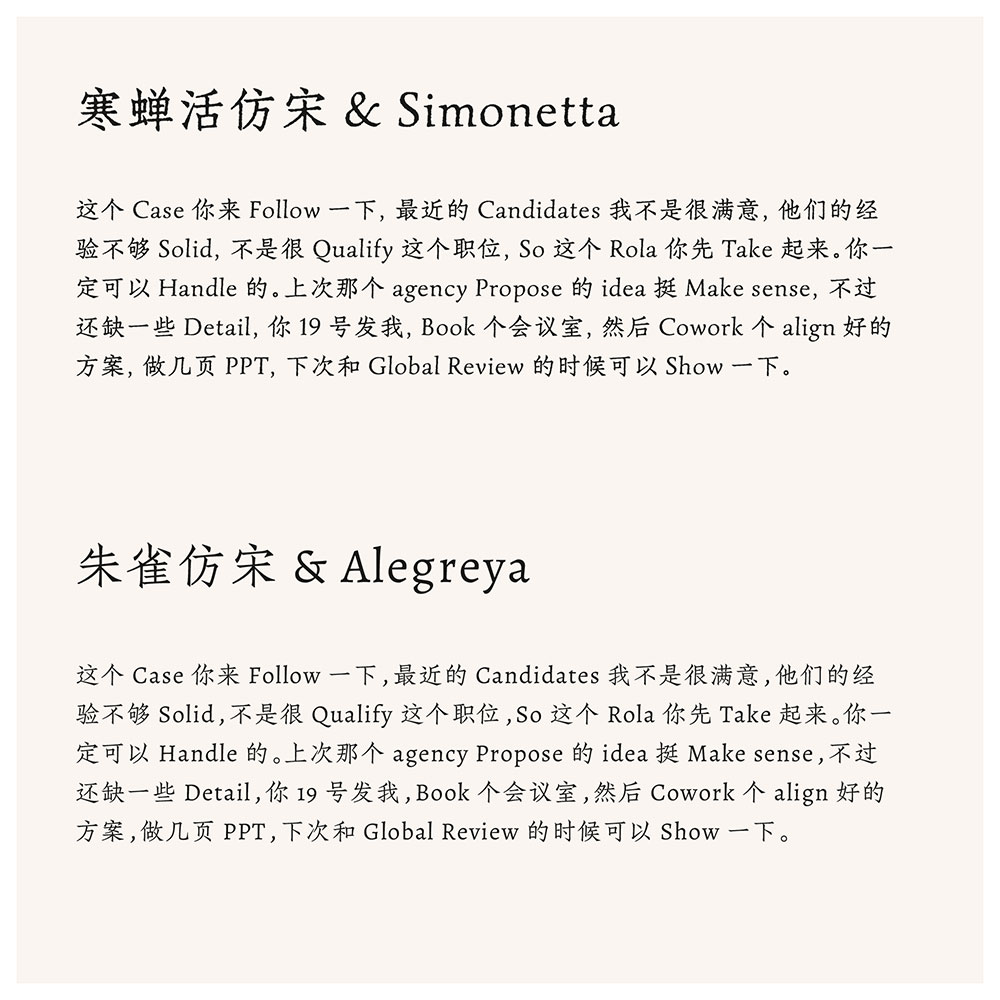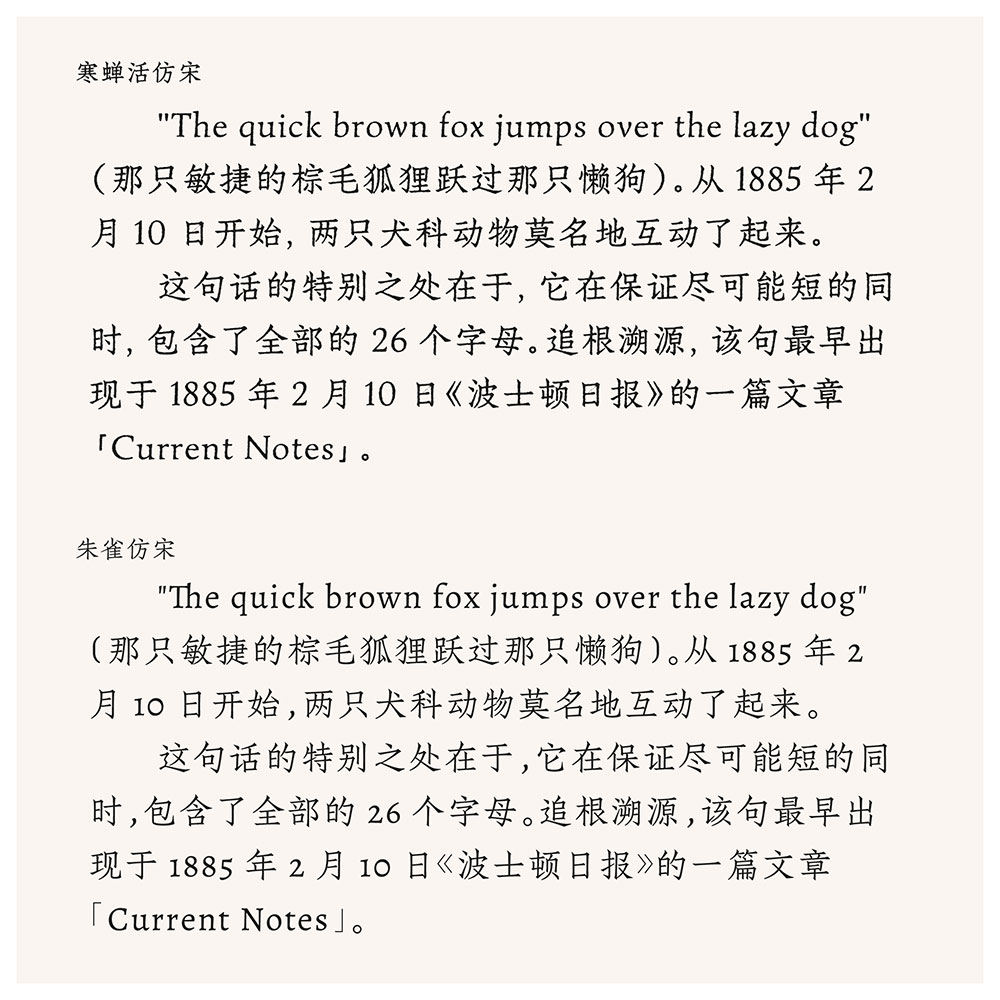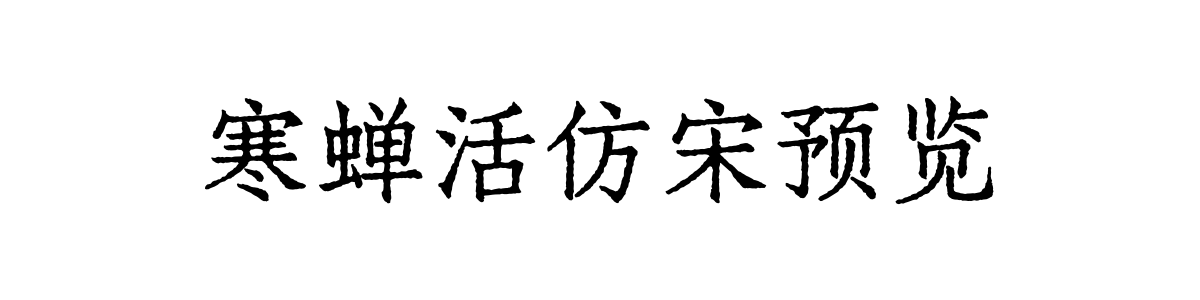
寒蝉活仿宋
寒蝉活仿宋(Chill Huo FangSong)是一款通过数字手段模拟活字印刷轻度油墨溢出效果,追求复古真实质感的开源字体,该项目在开源字体朱雀仿宋与西文衬线体 Simonetta 的基础上进行深度修改,属于“反向造字”——将原本清晰、顺滑的字体轮廓,刻意处理为带有驳杂曲线与不规则边缘的形态,以模拟传统铅字印刷时油墨在纸张上轻微晕染、扩散的独特效果。
为实现这一目标,字体增加了大量节点,导致文件体积较大,因此对字符集进行了精简,优先保留了网络常用的简体与繁体中文。同时,项目全新适配了西文部分并创建了配套标点。开发者明确表示,其效果与真实印刷扫描字体仍有差距,旨在取得一种轻度的、具有复古真实感的斑驳效果。
字体风格
寒蝉活仿宋旨在复现一种特定的物理媒介痕迹——活字印刷的“不完美”美感。通过数字技术,字体笔画边缘被塑造出细微的、不均匀的毛边和浸润感,仿佛油墨在纸张纤维间微微洇开;曲线部分被刻意打断为驳杂的节点,模仿铅字磨损或印刷压力不均带来的随机性。